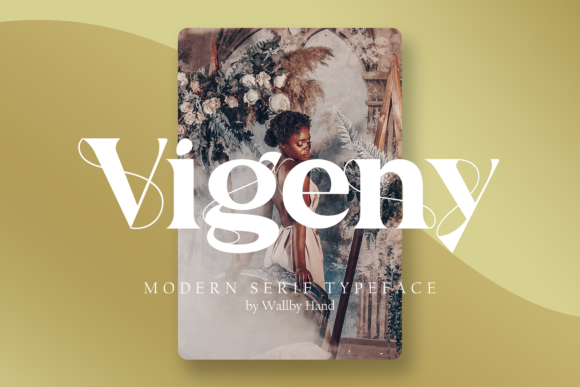
Creativefabrica Vigeny Font
[Creativefabrica] Vigeny Font
Vigeny - это современная засечка с уникальными персонажами.
Этот красивый и профессиональный шрифт подходит для плакатов, заголовков, печатных букв, подзаголовков, оформления логотипов, брендинга и многого другого.